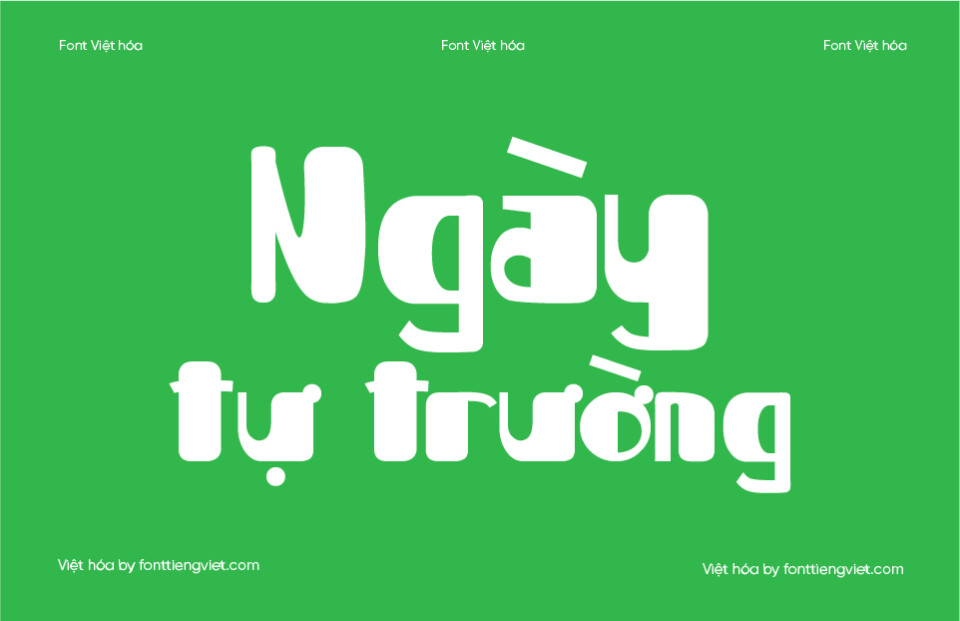
Font Việt hóa 1FTV Junior Schoolboy
Giới thiệu về Font Việt hóa 1FTV Junior Schoolboy
Trong thiết kế đồ họa dành cho lứa tuổi học đường, việc lựa chọn một Font Miễn Phí phù hợp đóng vai trò quan trọng trong việc truyền tải thông điệp. Font Việt hóa 1FTV Junior Schoolboy là một lựa chọn hoàn hảo, mang phong cách trẻ trung và đầy năng lượng. Được lấy cảm hứng từ những nét chữ viết tay tinh nghịch trên bảng đen, bộ font này giúp các bản thiết kế trở nên gần gũi và thân thiện hơn với học sinh.
Đặc điểm nổi bật của bộ font
Bộ Font Việt hóa 1FTV Junior Schoolboy sở hữu những đường nét dày dặn, mô phỏng kiểu chữ in đậm thường thấy trong các sách bài tập hoặc biển báo trường học. Điểm đặc biệt của phiên bản này là đã được tối ưu hóa bảng mã tiếng Việt, giúp người dùng dễ dàng gõ các dấu thanh mà không lo lỗi hiển thị. Với phong cách vui tươi, font chữ này không chỉ dùng để tiêu đề mà còn cực kỳ nổi bật trên các ấn phẩm cổ động.
Ứng dụng thực tế của Font Việt hóa 1FTV Junior Schoolboy
Sử dụng trong giảng dạy và học tập
Các thầy cô giáo có thể sử dụng Font Việt hóa 1FTV Junior Schoolboy để thiết kế slide bài giảng Powerpoint hoặc trang trí báo tường. Sự rõ ràng của các ký tự giúp học sinh dễ dàng theo dõi nội dung từ xa. Bên cạnh đó, các bậc phụ huynh cũng có thể dùng font này để làm nhãn vở hoặc thiệp mời sinh nhật cho con em mình, tạo nên sự độc đáo và cá tính riêng biệt cho các bé.
Thiết kế truyền thông học đường
Ngoài ra, font chữ này còn rất được ưa chuộng trong việc thiết kế áo đồng hồ, logo câu lạc bộ hoặc các poster sự kiện thể thao tại trường. Tính linh hoạt và sự khỏe khoắn trong từng nét chữ giúp tạo ra bầu không khí năng động, khuyến khích tinh thần sáng tạo của giới trẻ hiện nay.
Kết luận về bộ font chữ học đường
Có thể thấy, việc sở hữu bộ Font Việt hóa 1FTV Junior Schoolboy sẽ giúp kho tài nguyên thiết kế của bạn trở nên phong phú hơn bao giờ hết. Nếu bạn đang tìm kiếm sự kết hợp giữa tính ứng dụng và thẩm mỹ giáo dục, đừng bỏ qua cơ hội sở hữu Font Miễn Phí, Font Việt Hóa, Font Việt hóa 1FTV Junior Schoolboy ngay hôm nay để bắt đầu những dự án đầy thú vị của mình.